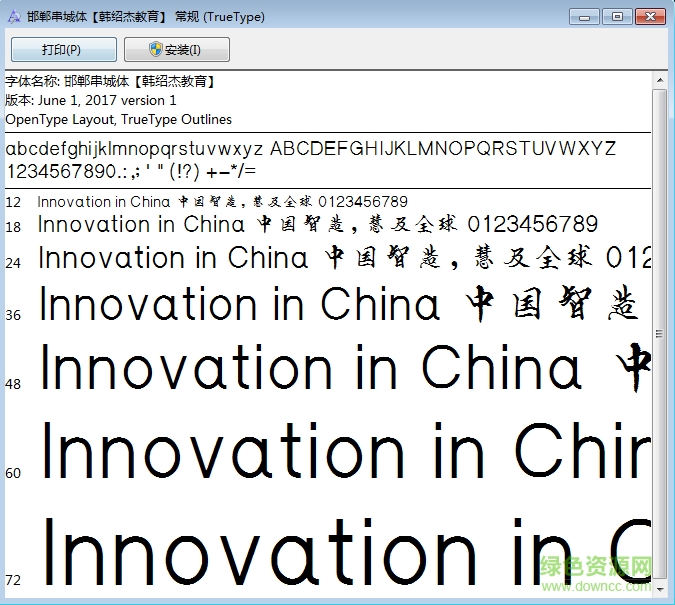
漢標串城體字體是一款造型精簡、用筆溫婉的毛筆書法字體,收錄在漢字體中,具有古典藝術(shù)字體的飄逸和現(xiàn)代字體的時尚,給設(shè)計帶來更加精彩的呈現(xiàn),綠色資源網(wǎng)今日推薦!
漢標串城體采用了串城街邯鄲道的本地風格氣息,為用戶帶來正宗的老城風味特色,讓文字蘊含無窮的底蘊和故事背景,給設(shè)計師的創(chuàng)作帶來更加精彩的增色!
漢標串城體字體筆畫清雅秀麗,給人整潔大方的感覺,字體整體效果非常出色,適合應(yīng)用于廣告設(shè)計、名片設(shè)計、包裝印刷、產(chǎn)品設(shè)計等應(yīng)用。